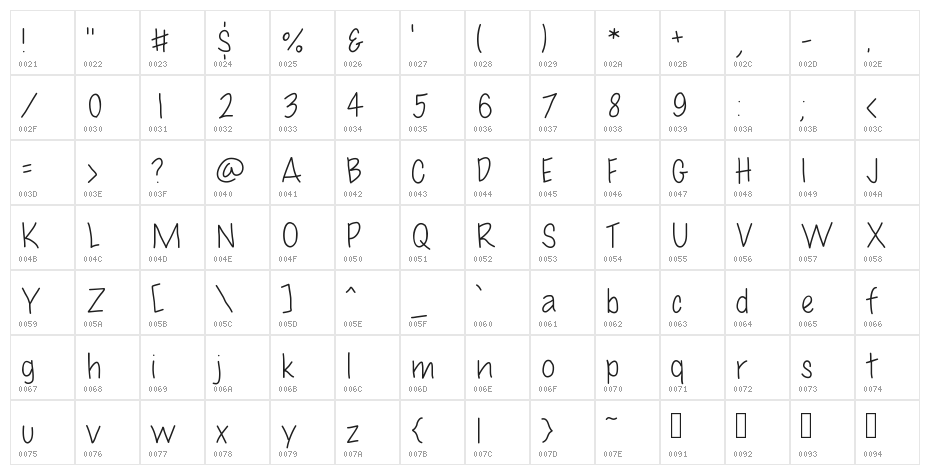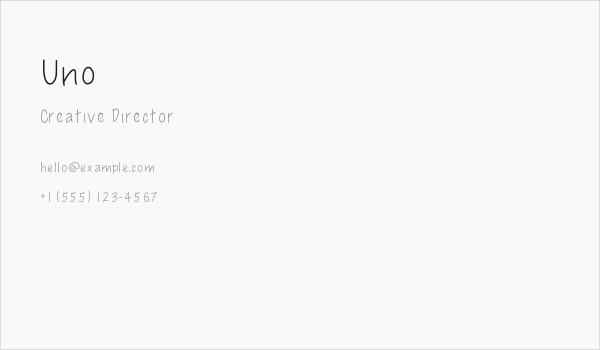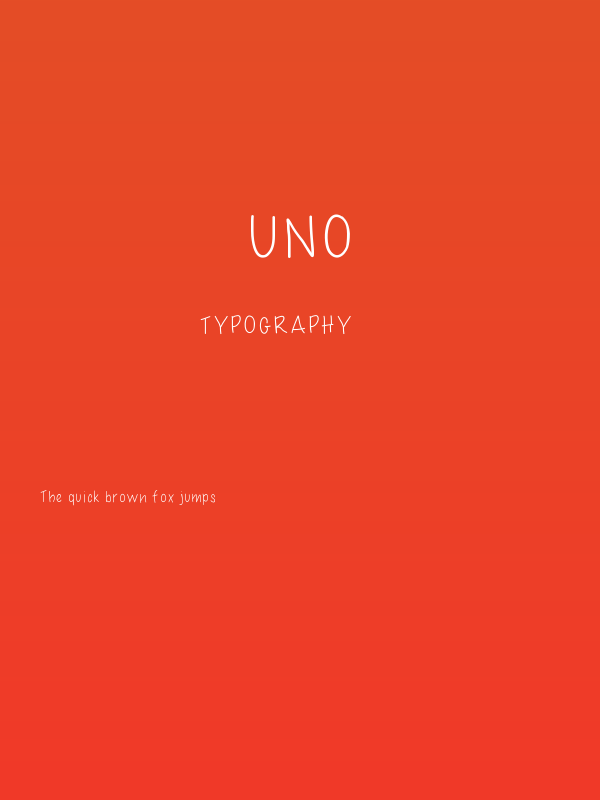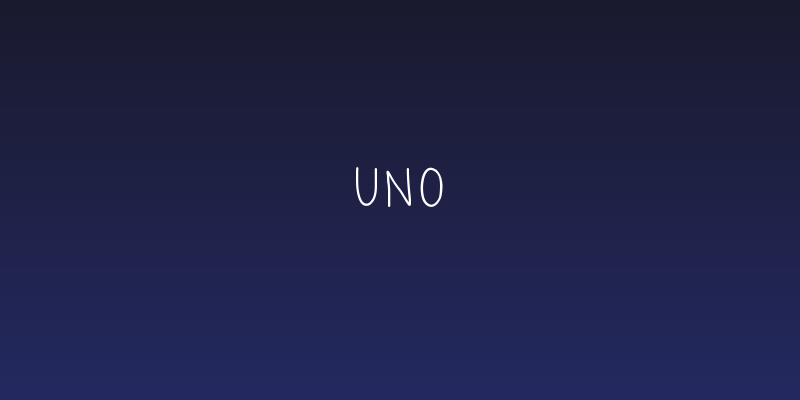
Uno Font
UNO MAIUSCOLE
UNO MINUSCOLO
UNO ALTRI CARATTERI
| Stile generale | Casual |
| Caso d'uso | Headlines, Informal text, Creative projects |
| Progetti proposti | Ideal for greeting cards, children's books, personal blogs, and casual branding projects. |